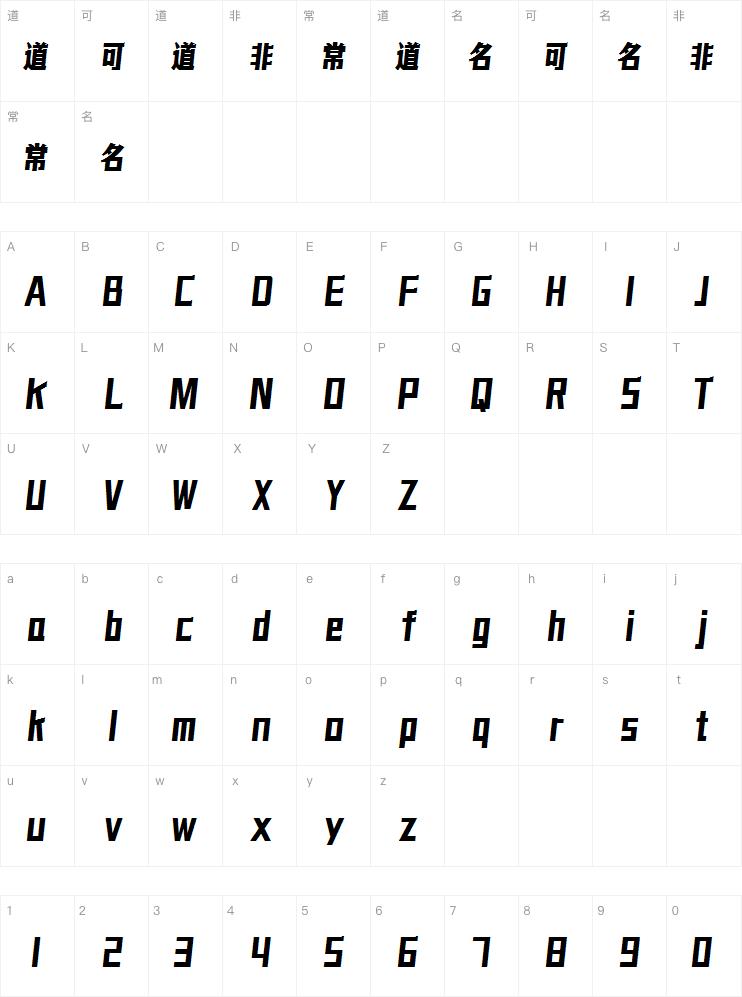
卓特悦动黑
卓特清雅体是卓特视觉(droitstock.com)携手国内知名字体设计师刘兵克为创意人群打造的开源字体。 这款字体字形高挑、倾斜,笔画坚实,呈现出强烈的力度感和动势,带着一种“向前推进”的速度感,这款字融合了近代印刷美术字的装饰特征,横画外侧加以尖角装饰,让人联想到民国书刊、老招牌上的题字。非常适合用于标题、海报、运动赛事、游戏视觉、潮流品牌等需要张力与存在感的场景,让信息以更直接、更冲击的方式抵达视觉中心。 本字体包含 GB2312-80 标准中的 6763 个简体汉字及 420 个常用字符,共收录 7183 个字符,可免费商用。